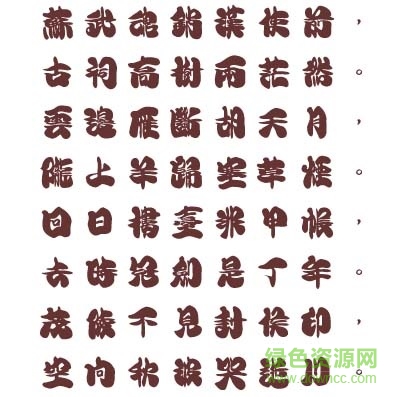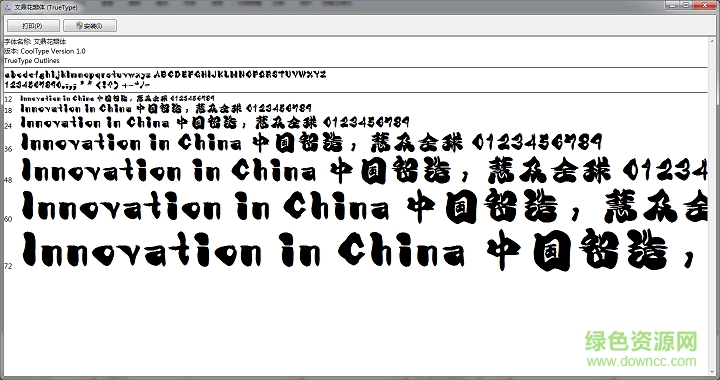
文鼎花瓣體是一款極具特色和創(chuàng)意的簡體字體。該字體的字形像花瓣一樣,非常的美麗,是美工們的必備字體啊!有需要的用戶趕快下載體驗(yàn)吧!
1、略高于普通視覺重心的設(shè)計(jì),讓字看起來更精神,更挺拔。
2、筆畫的平行設(shè)計(jì),令標(biāo)題綜藝也有了手寫味道,如同橫排筆刷的杰作。
3、塊面感更強(qiáng),塊狀視覺沖擊力更利于延展變形。
4、92%的字面大小,讓粗壯的字與字之間達(dá)到均衡的分白效果。有作為標(biāo)題絕佳的整體感。